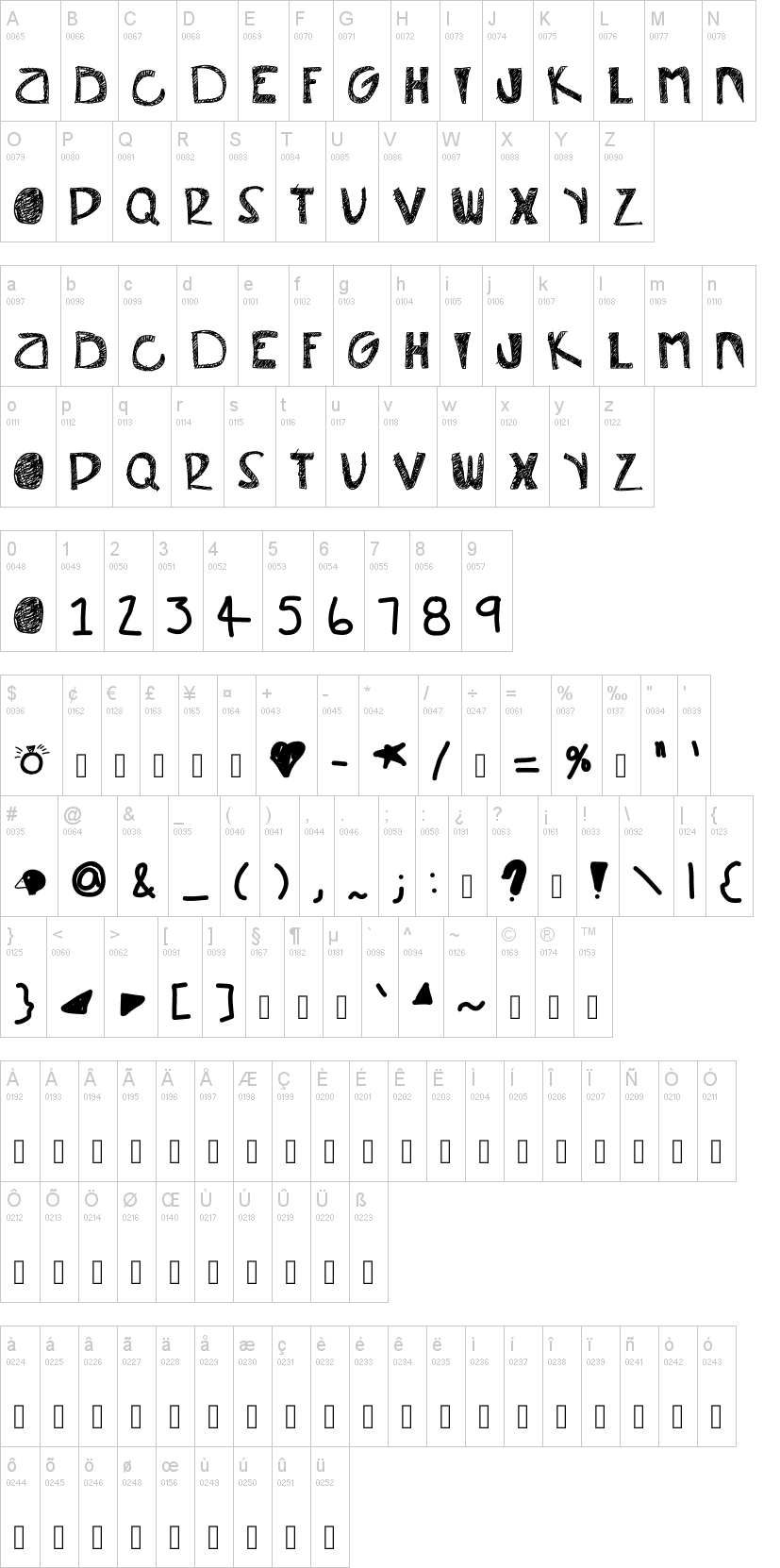
Misunderstood 是一种手写字体,由设计师 Misprinted Type 创建。该字体的特点是字母笔画的不规则和不对称,给人一种手工制作的感觉,同时也蕴含了一种艺术气息。 Misunderstood 字体适用于许多设计项目,尤其是与手工制作、手写信件、卡片、海报和标志相关的项目。它的个性化和独特性使它成为一个非常受欢迎和流行的字体选择。 此外,Misunderstood 字体也有多种样式可供选择,包括常规、斜体、粗体和粗斜体,可以满足各种排版需求。内容介绍
Misunderstood是一款非常不错的手写艺术字体,具有很好的视觉感,适合于文化类的宣传设计、商业类品牌的广告和产品包装设计以及个性化文字排版等较多场景。